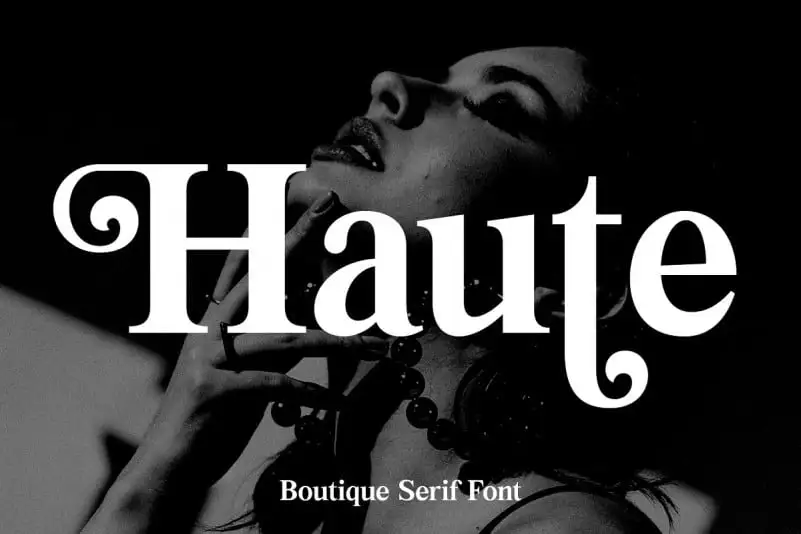
A Haute Serif Font é uma combinação entre a elegância dos caracteres serifados da década de 1970 moderna ou vintage e o estilismo contemporâneo, criando um conjunto único que transmite sofisticação e estilo. Este tipo de fonte inclui todos os caracteres normais que você espera encontrar em uma tipografia completa, além de caracteres multilinguas para facilitar a comunicação internacional. A Haute Serif Font também oferece uma vasta seleção de caracteres alternativos para as letras maiúsculas, permitindo um grau adicional de personalização e criatividade nas criações digitais. Estes detalhes adicionais tornam a fonte uma opção versátil e interessante tanto para uso profissional quanto em projetos de design pessoal.